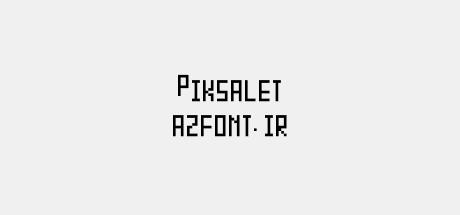
فونت زیبای رایگان Piksalet
قلم زیبای Piksalet از سری قلم های بسیار زیبا برای تایپوگرافی و لوگو تایپ می باشد.این قلم در وزن Regular و توسط Muhammad Hacen طراحی و منتشر شده است.